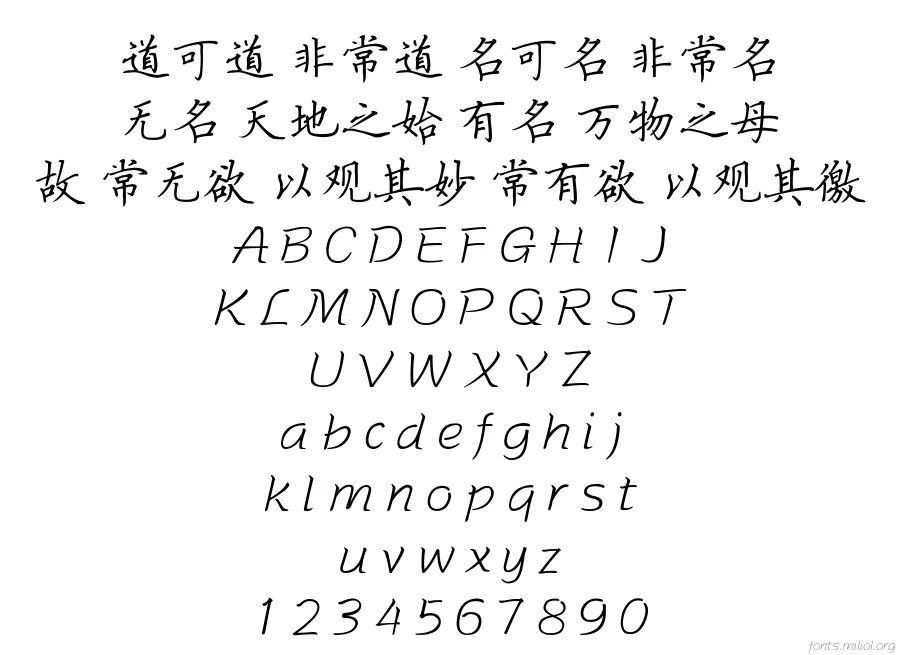
## 方正硬笔楷书_GBK:传统书法与现代数字的完美融合
方正硬笔楷书_GBK是一款兼具传统书法韵味与现代实用性的电脑字体,它将中国传统的硬笔楷书艺术完美地移植到数字时代。这款字体保留了硬笔书法的独特笔触和结构特点,每一笔划都展现出刚劲有力的书写风格,同时通过数字化处理确保了文字的清晰度和可读性。
作为GBK编码字体,它完整支持20902个汉字字符,满足各类中文文档的排版需求。其笔画粗细均匀、结构严谨的特点,特别适合正式文书、教育材料等需要体现端庄稳重的场合使用。字体的设计既传承了中国书法艺术的精髓,又符合现代印刷字体的规范标准,在传统与现代之间找到了绝佳的平衡点。
这款字体的推出不仅为电脑字库增添了新的艺术选择,更为推广中国书法文化提供了数字化载体,让更多人能够便捷地感受硬笔楷书的独特魅力。
方正硬笔楷书_GBK 字体映射图